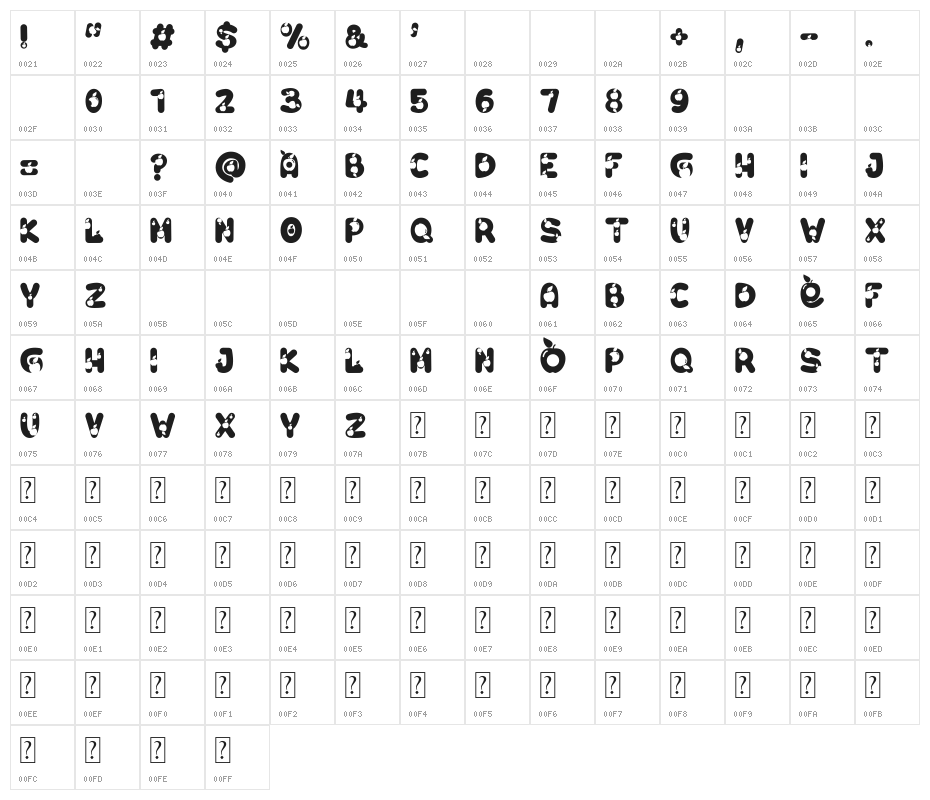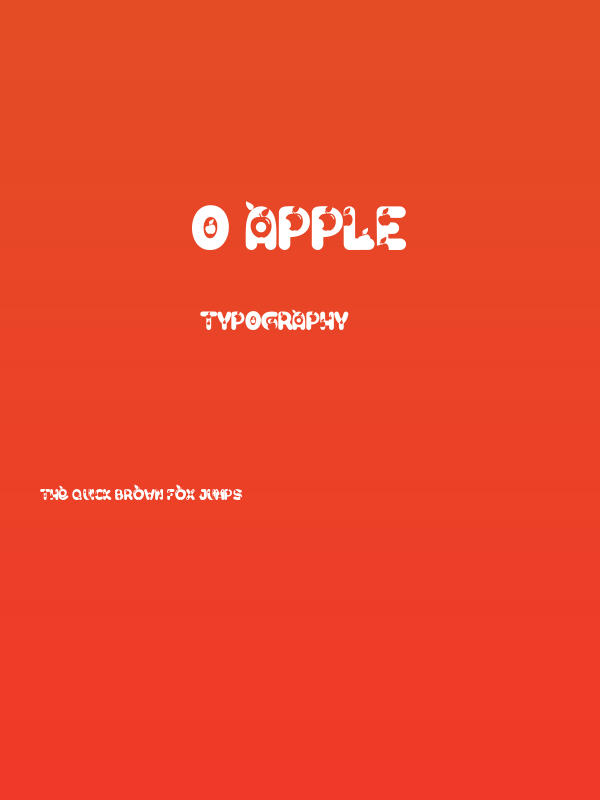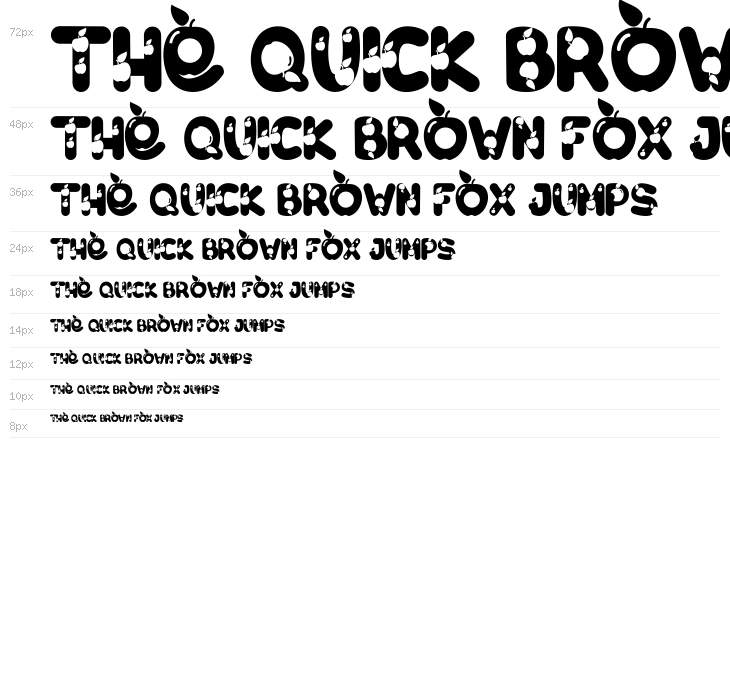
O Apple Font
| Stile generale | Modern, Decorative |
| Progetti proposti | Ideal for children's book covers, playful branding, food-related designs, and creative posters. |